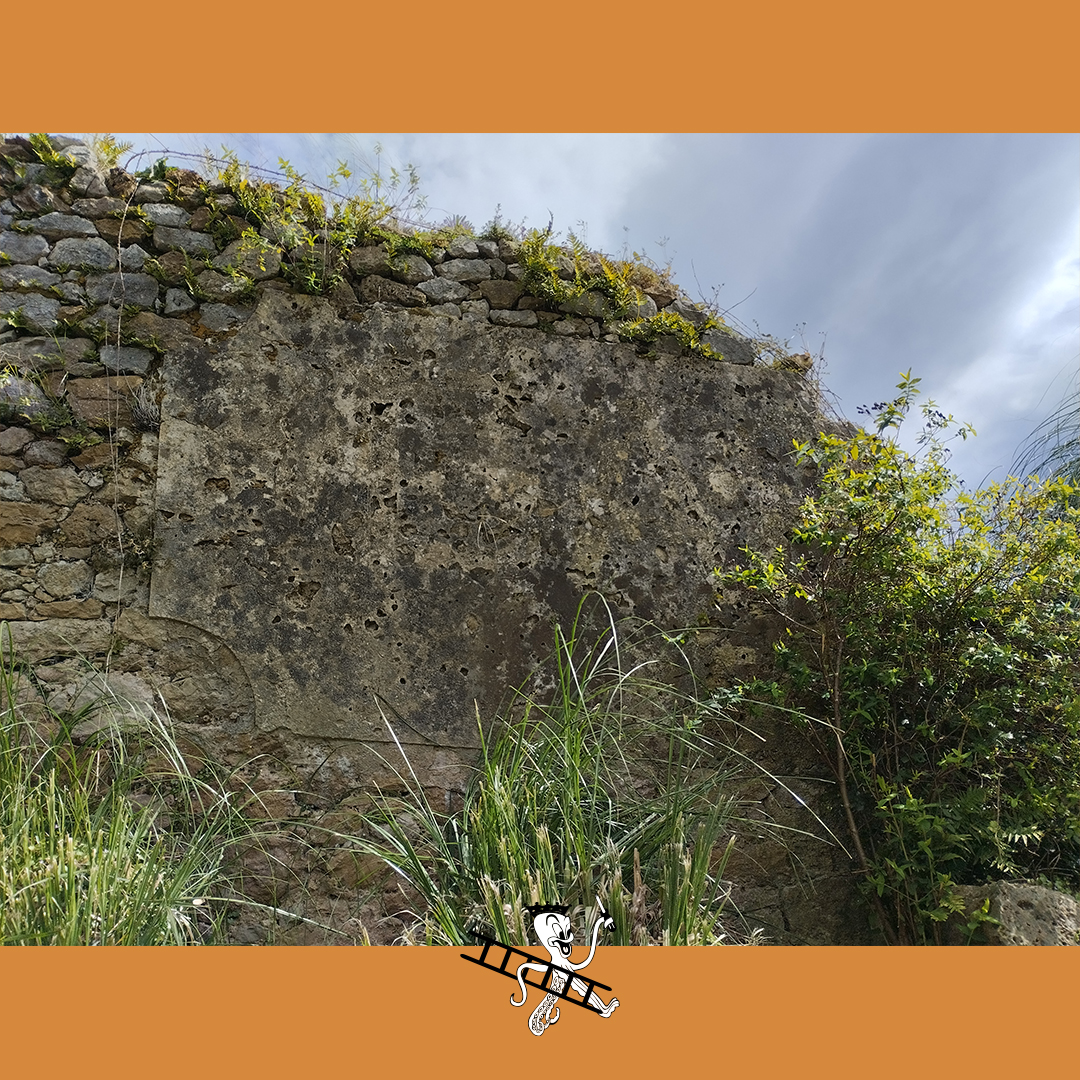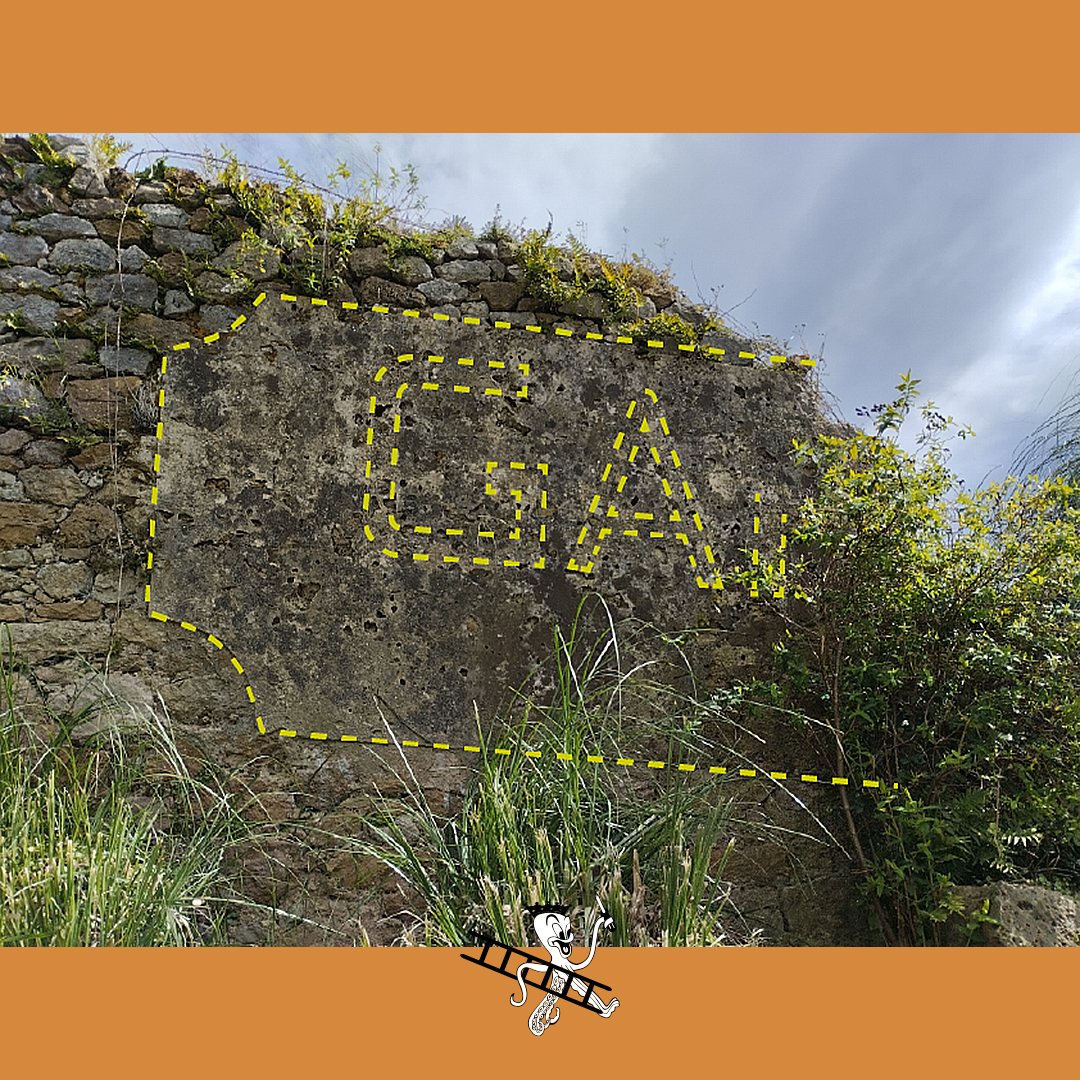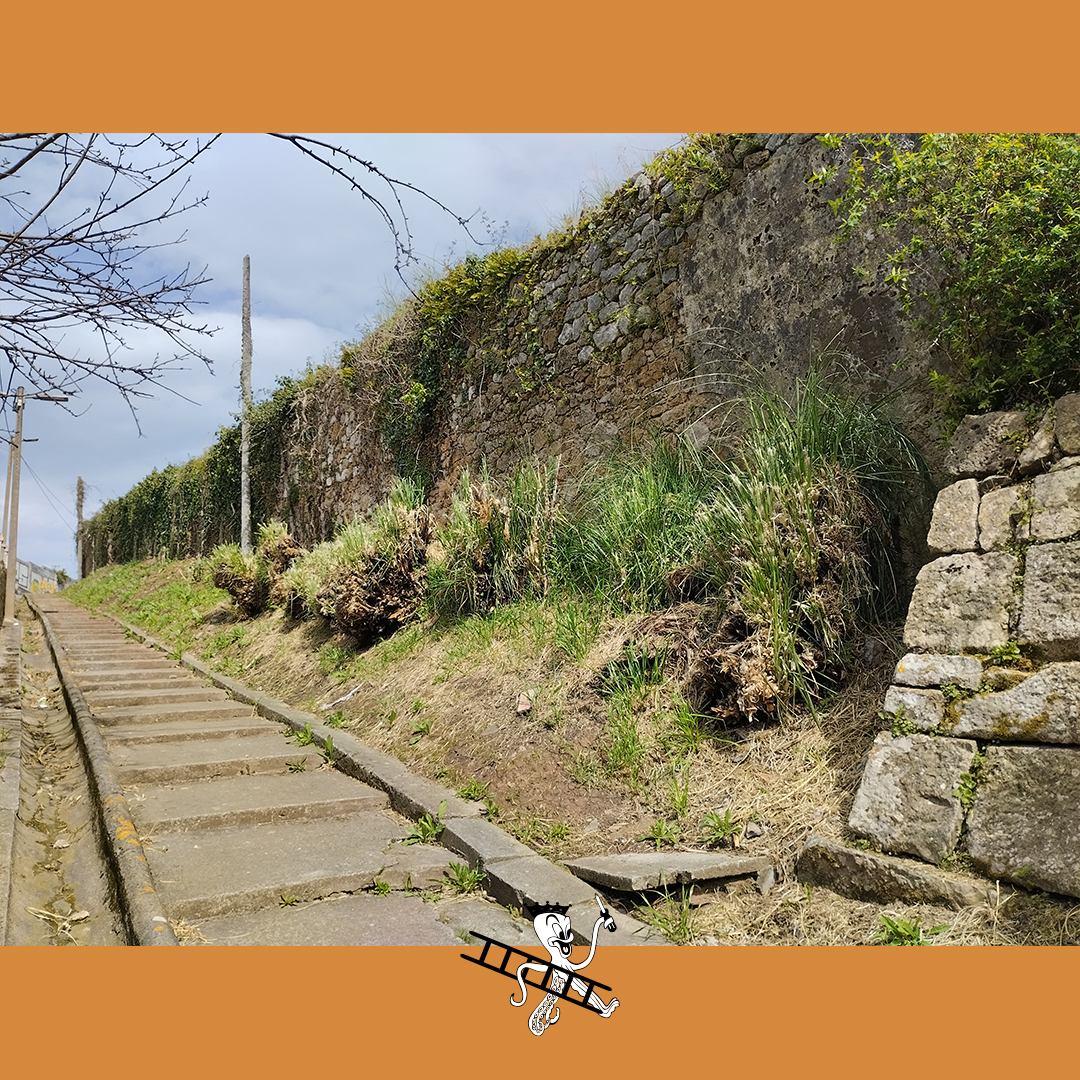
Rótulo Fantasma en Peñacastillo
Este rótulo fantasma (Ghostsign) está en Peñacastillo; justo en las escaleras que conectan Eduardo Garcia del Rio con Campogiro, donde hay un muro donde que se ve una placa con moldura y el negativo de las letras «GA». Parece haber otra, pero será necesario examinarlo con calma.
Mientras tanto ya se ha buscado en mapas de época en mapas.cantabria.es y no aparece estructura alguna anterior a 1946 (1ª referencia disponible). Se sabe que esa zona ha sido industrial desde mediados del siglo XIX.